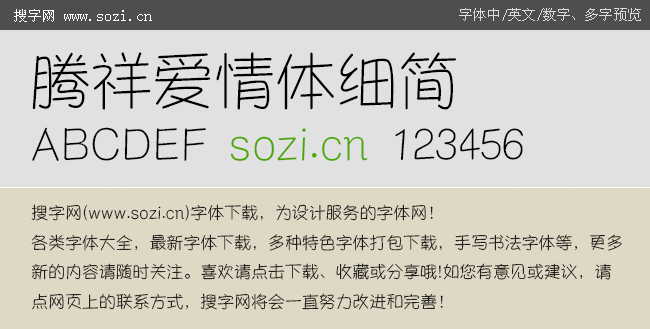
騰祥愛(ài)情體細(xì)簡(jiǎn)
搜字網(wǎng)提供一款騰祥愛(ài)情體細(xì)簡(jiǎn)中文藝術(shù)字體下載,騰祥愛(ài)情體是一款字跡輕柔溫和的騰祥字體,筆畫(huà)輕松、結(jié)構(gòu)疏緩,使文字表達(dá)更加貼心與無(wú)微不至。本款字閱讀流暢、筆畫(huà)舒展富于朝氣與生機(jī)。適合數(shù)字媒體、包裝設(shè)計(jì)、廣告設(shè)計(jì)、網(wǎng)頁(yè)設(shè)計(jì)等設(shè)計(jì)場(chǎng)合使用。